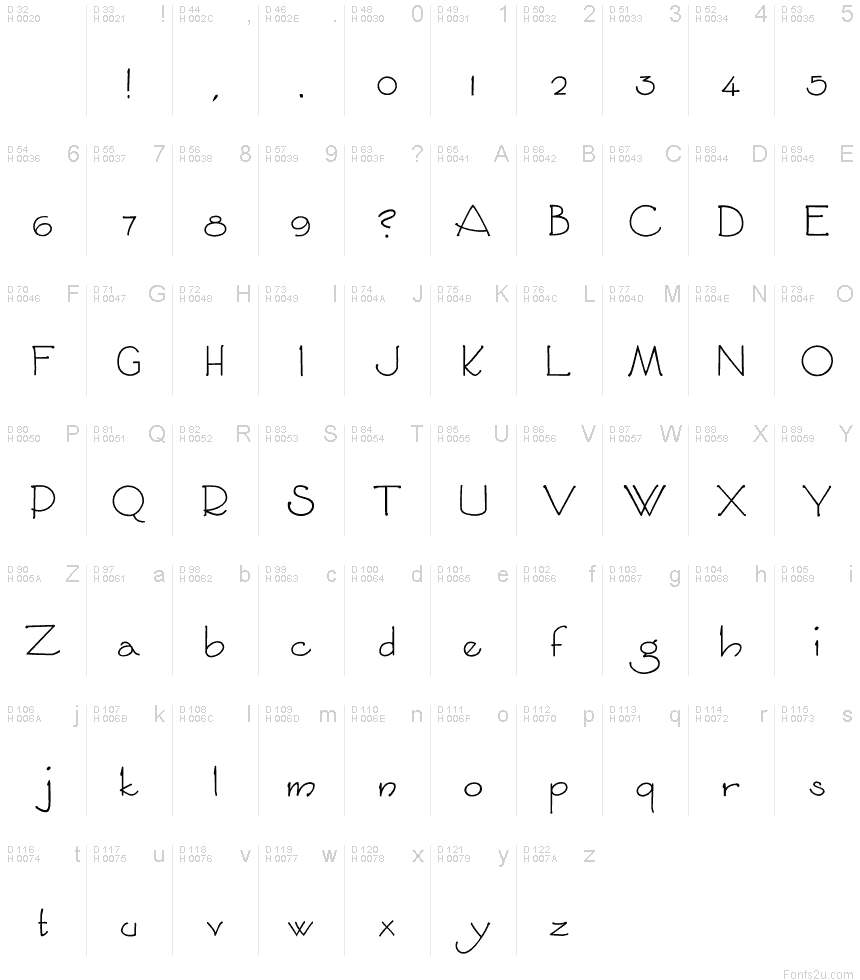
خط Sycamore Sans من تصميم Sam Wang هو خط كتابة يدوي مجاني ذو خط أحادي ومنحنيات طويلة ومرنة بأسلوب رسومي عفوي بالقلم. تتغير اتجاهات ضرباته الدقيقة بسلاسة، مع حلقات عريضة وأشكال حروف مفتوحة برقة.
تتناغم الرسوم النباتية الخطية مع الخطوط المتפתحة للحروف، مما يجعله خياراً طبيعياً لهوية العلامات التجارية للحدائق وتغليف البذور. كما تتناسب الأشكال المريحة مع قوائم طعام المقاهي والقرطاسية الشخصية. وتعد حركته التي تشبه الكرمة مناسبة بشكل خاص للمطبوعات ذات الطابع الطبيعي والرسوم الفولكلورية اللطيفة.